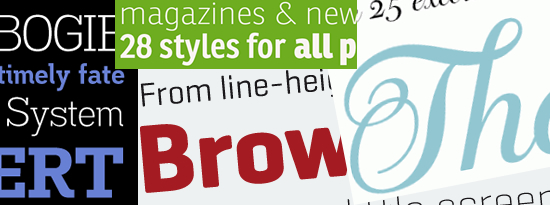
30 brillante tipografías para el diseño corporativo
El diseño de un buen tipo de letra, que sea legible, es un trabajo duro y requiere tiempo y paciencia. Una tipografía tiene que transmitir un mensaje claro y eficaz, independientemente del entorno en el que se utiliza. Por supuesto, existen miles de tipos de letras que gratuitas disponibles en Internet, y algunas de ellas a pesar de que son gratuitas son de gran calidad, una buena muestra la puedes encontrar en el artículo
40+ Excellent Freefonts For Professional Design. Sin embargo, sólo unas pocas tipografías gratuitas tienen un aspecto profesional cuidadosamente diseñado, que han sido desarrolladas a lo largo de años, con una estrecha atención a pequeños detalles.
El autor del articulo
30 Brilliant Typefaces For Corporate Design, de
SmashingMagazine, ha realizado un análisis sobre la tipografía más popular que se han publicado recientemente, que se han recomendado con frecuencia, mencionado o discutido en blogs, foros y revistas. Al final, han realizado una completa lista de las empresas más prometedoras, con los tipos de letras y la información recogida sobre cada uno de ellos. El resultado es este amplio escaparate de los tipos de letra, junto con enlaces a información sobre precios y muestras.
Encontraremos 35 nuevos tipos de letra para realizar brillantes diseño corporativo.
Debemos tener en cuenta que no son gratuitas, y se han centrado en los
tipos de letra que realmente vale la pena gastarse dinero en ellas. Una muestra que puede servir como
referencia para los diseñadores profesionales que buscan tipografía nueva para sus proyectos de empresas.